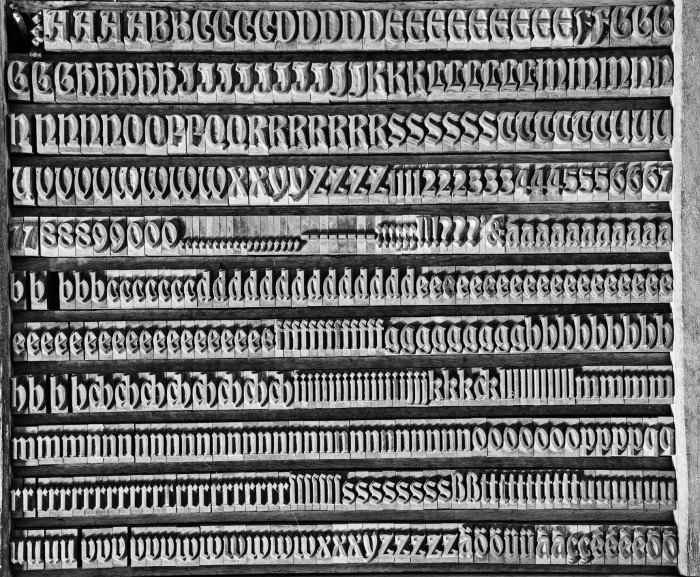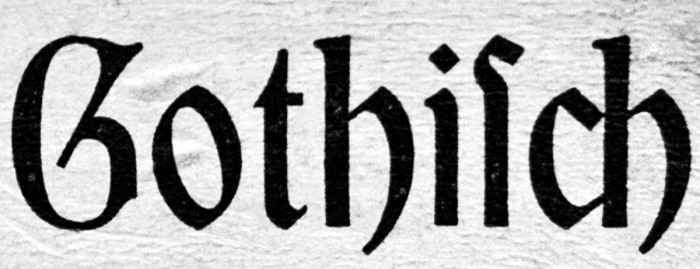
Weitere unbekannte gebrochene Bleischrift
nach meiner vorigen Anfrage zur Identifikation einer überaus verzierten gebrochenen Schrift, die ich in Blei hier stehen habe, möchte ich jetzt nach einer weiteren gebrochenen, allerdings deutlich schlichteren Schrift fragen. Ich habe sie ebenfalls in Blei hier vorliegen, und in der Tat stammen beide aus demselben Kasten, der wohl ein Dachbodenfund war und den ich vor einiger Zeit gekauft habe. Ich hänge zwei Bilder an die Anfrage: wieder ein Foto der Beschriftung des Kastens und ein Übersichtsbild über den gesamten Bestand. Vielen Dank für hilfreiche Hinweise zur Benennung dieser Schrift!
In diesem Fall kann ich direkt eine Lösung anbieten:
Es ist die Altgotisch Mager von Berthold (die allerdings auch von anderen Gießereien (fast) identisch angeboten wurde, diese ist wiederum eine Kopie der "Bradley-Schrift" von ATF.
Hier gleich die erste.
(Übrigens hab ich die im Handbuch der Frakturschriften vom Hendlmeyer gefunden, welches, als ich nach dem Buch griff seltsamerweise genau bei der Bradley-Schrift aufklappte - Zufälle gibts...)
In Blei (und Holz) hatte diese Schrift von den verschiedenen deutschen (Nachmacher-)Gießereien unterschiedliche Namen bekommen - u.a. Amerikanische Gotisch, Altgotisch, Britannia, Globus, Original-Altgotisch u.a.